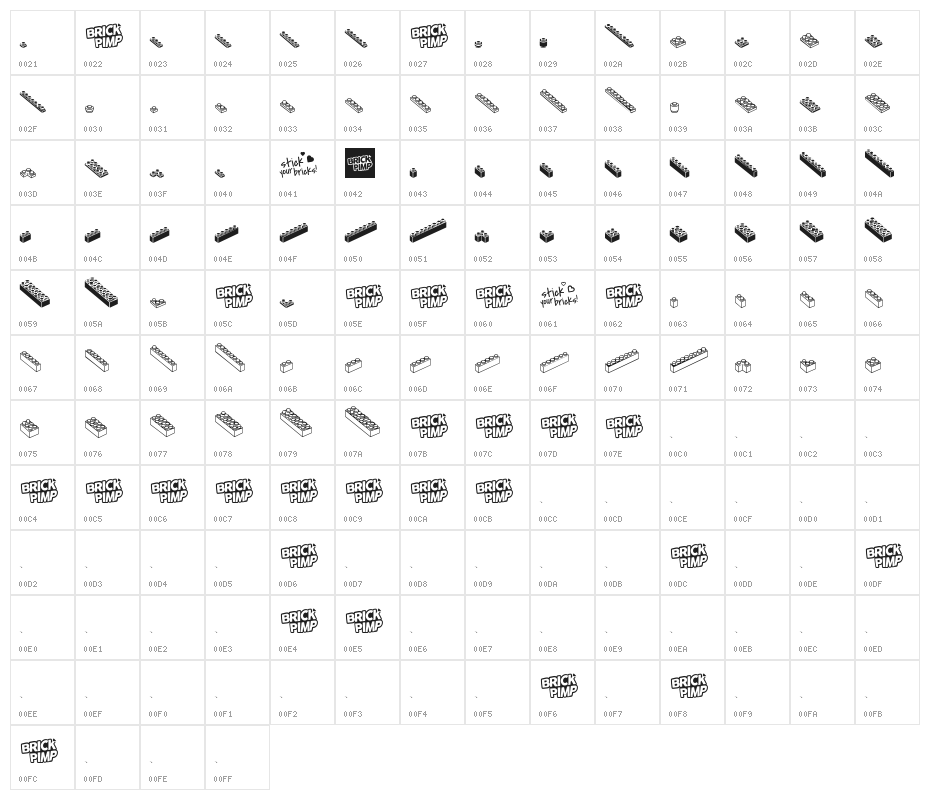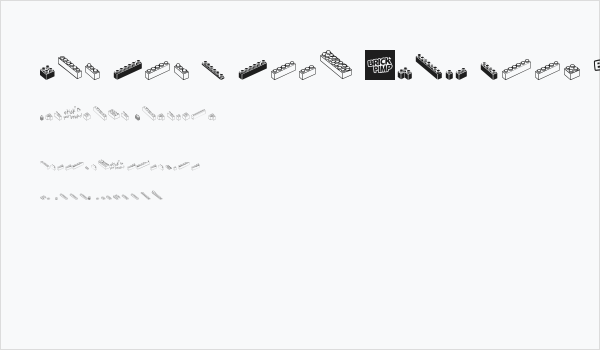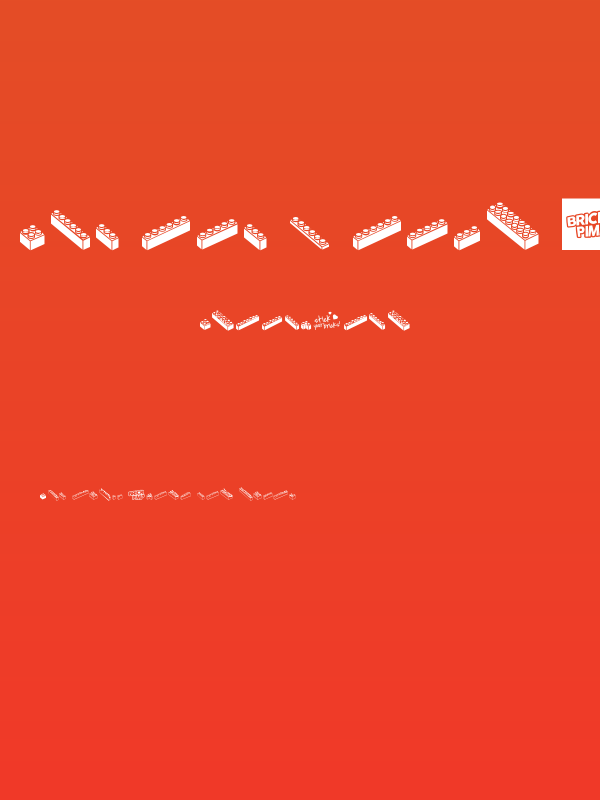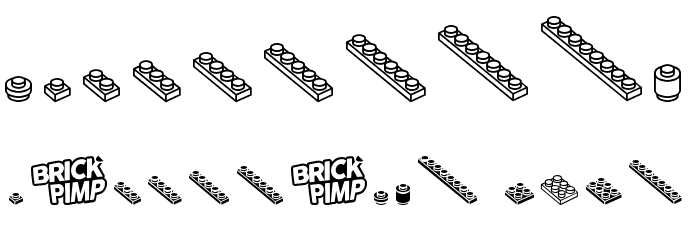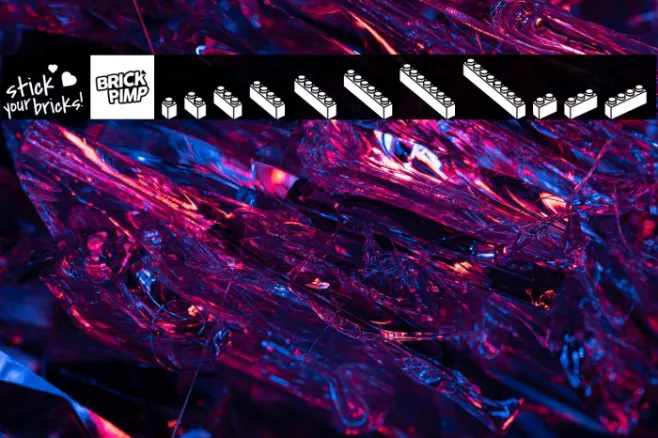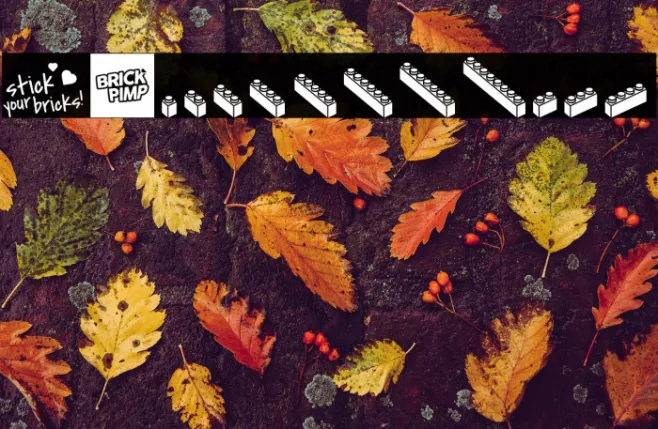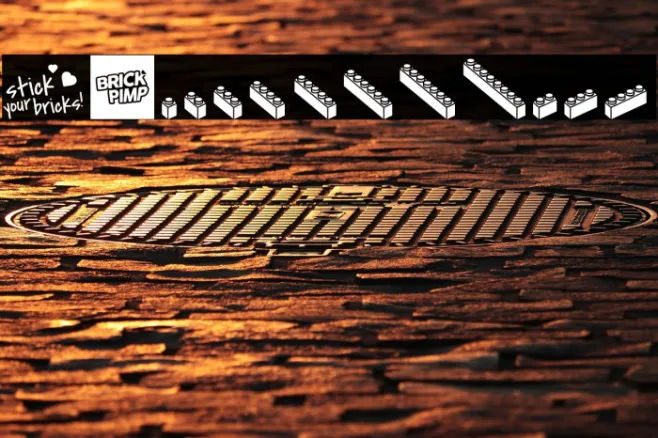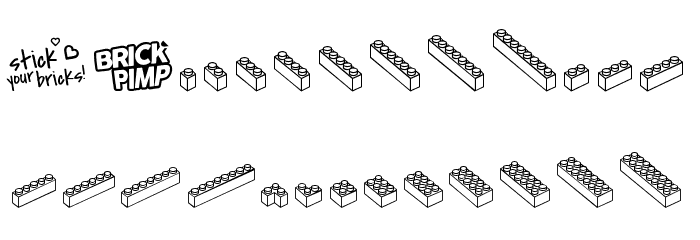
The One & Only BRICK Font b Font
| Gesamtstil | Playful, Creative, Nostalgic |
| Anwendungsfall | Logos, Headlines, Display text |
| Vorgeschlagene Projekte | Ideal for children's books, toy packaging, playful branding, and creative design projects. |